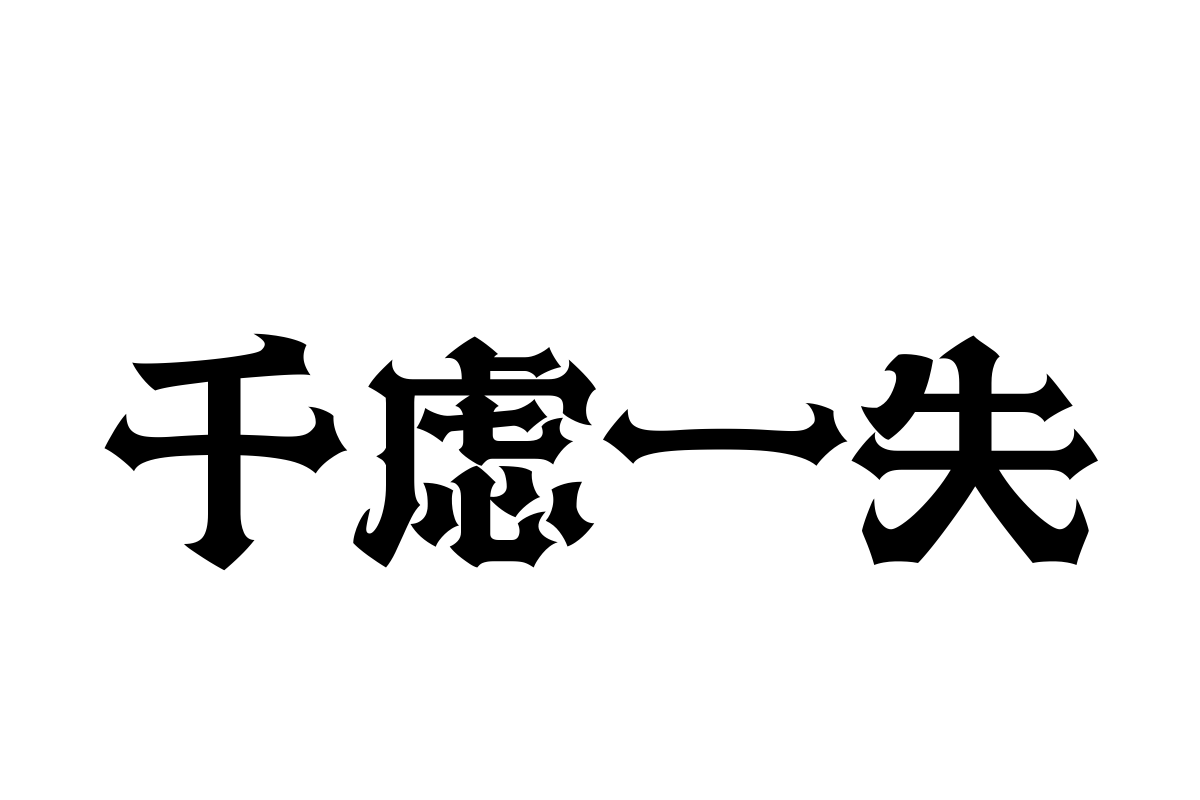
汉仪寒冰曲是一款具有暗黑、凌冽、魔幻、惊悚和尖锐风格的标题字。设计师打破了传统字体的笔型和结构,将笔画凝练为简洁的几何图形,使得字体的重心稳定一致,结构空间均衡,字面趋于方形,整体感觉稳重规整。
字体的重心略微偏上,使得整体视觉中心更加稳定。结构空间均衡,避免了视觉上的拥挤感。字面趋于方形,增加了字体的稳定性和可读性。起笔、收笔和转折处都设计成锐利的“尖钩”造型,看起来锋利,攻击性十足,给人一种强烈的视觉冲击。
总的来说,汉仪寒冰曲字体以其独特的哥特风格和强烈的视觉冲击力,成为了设计领域中不可多得的字体。无论是用于商业还是艺术设计,它都能展现出独特的魅力和价值。